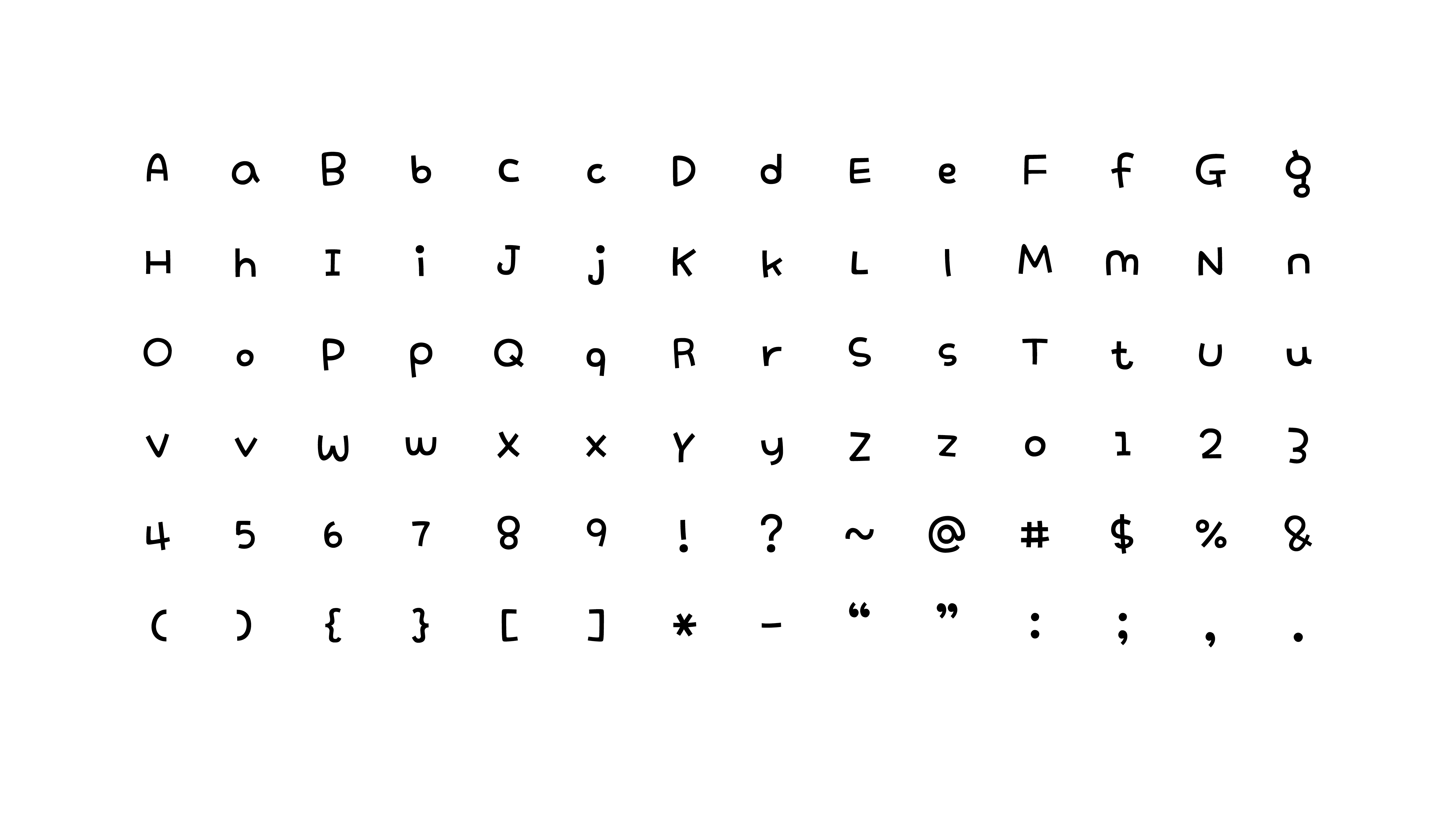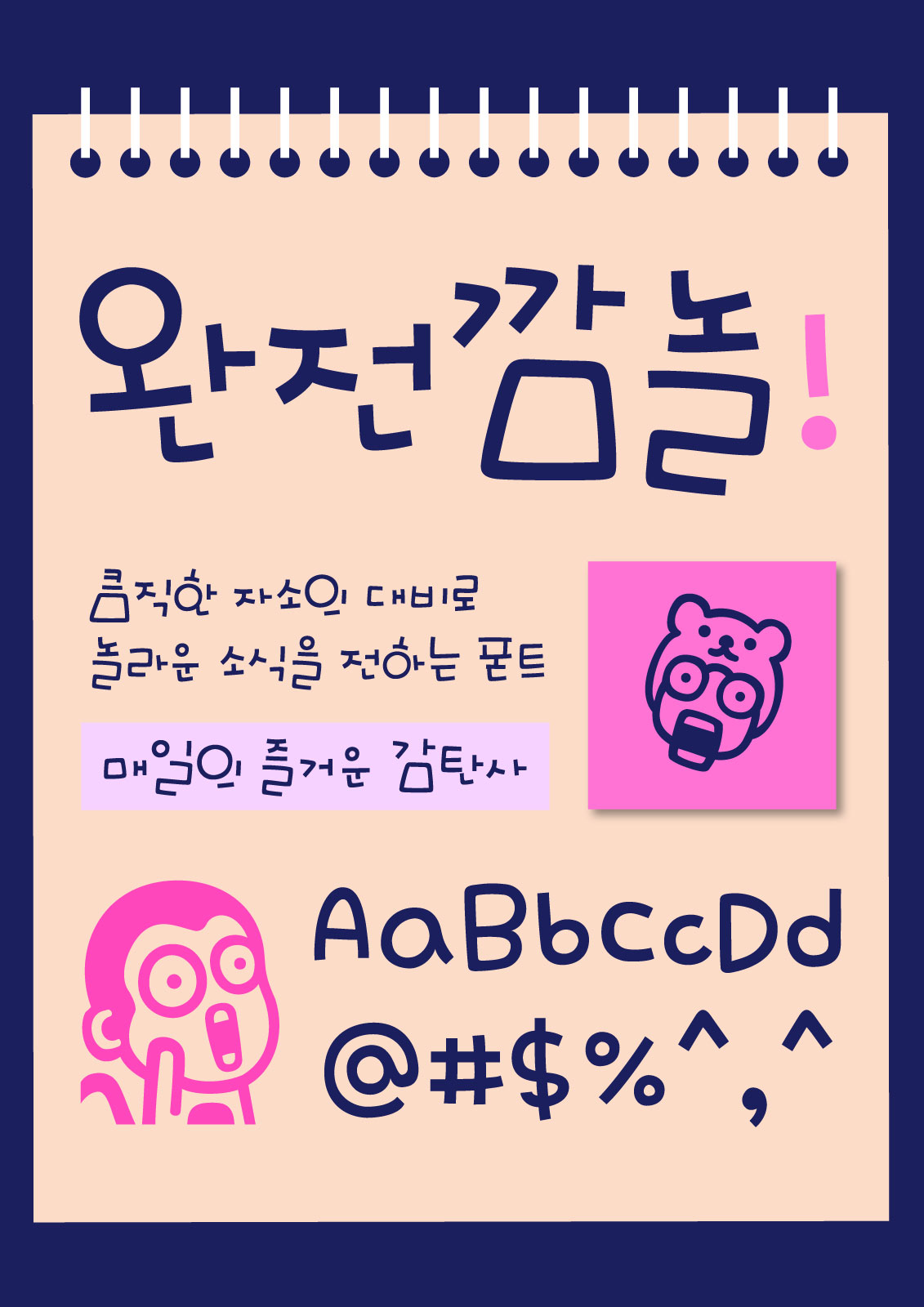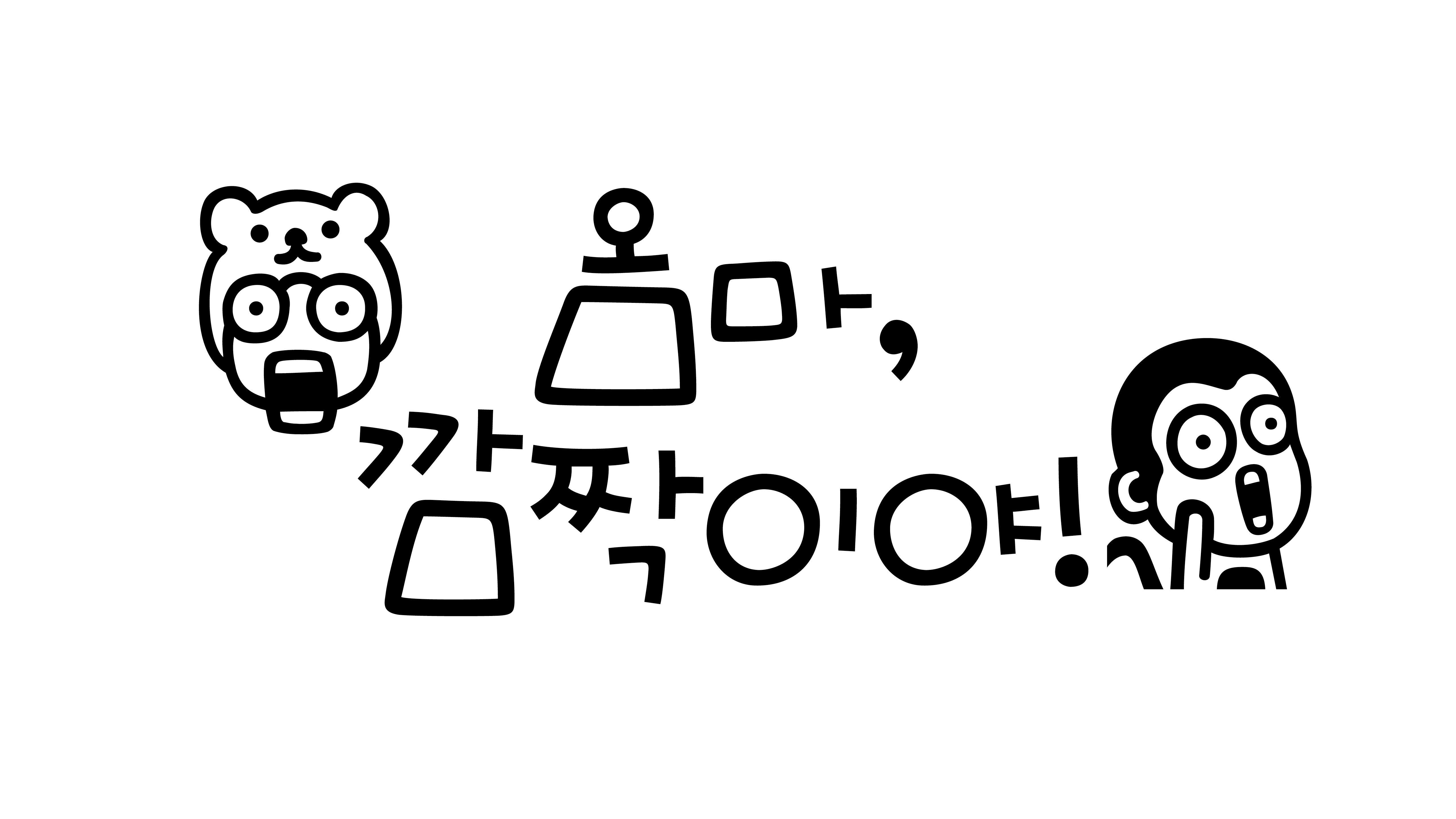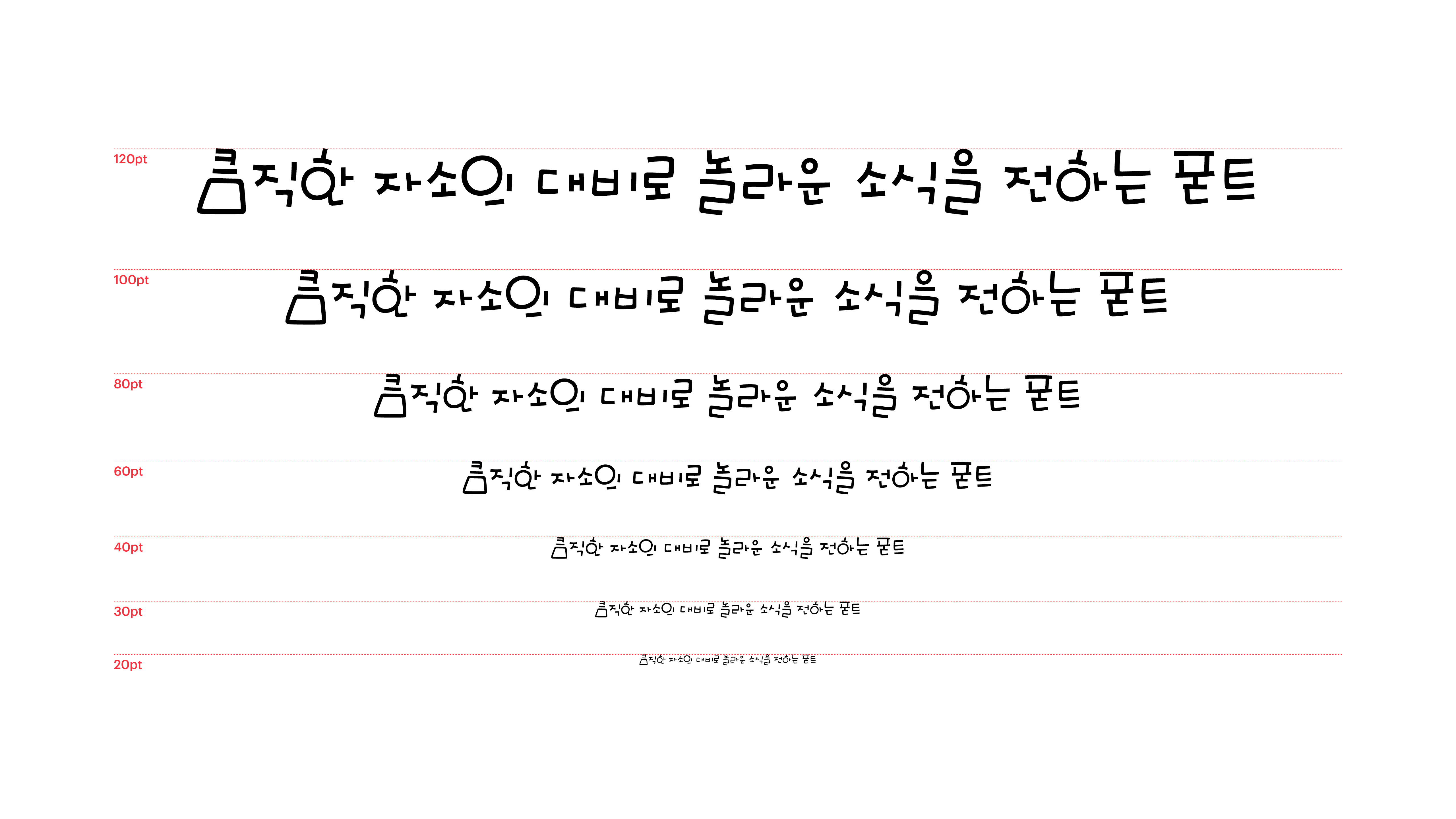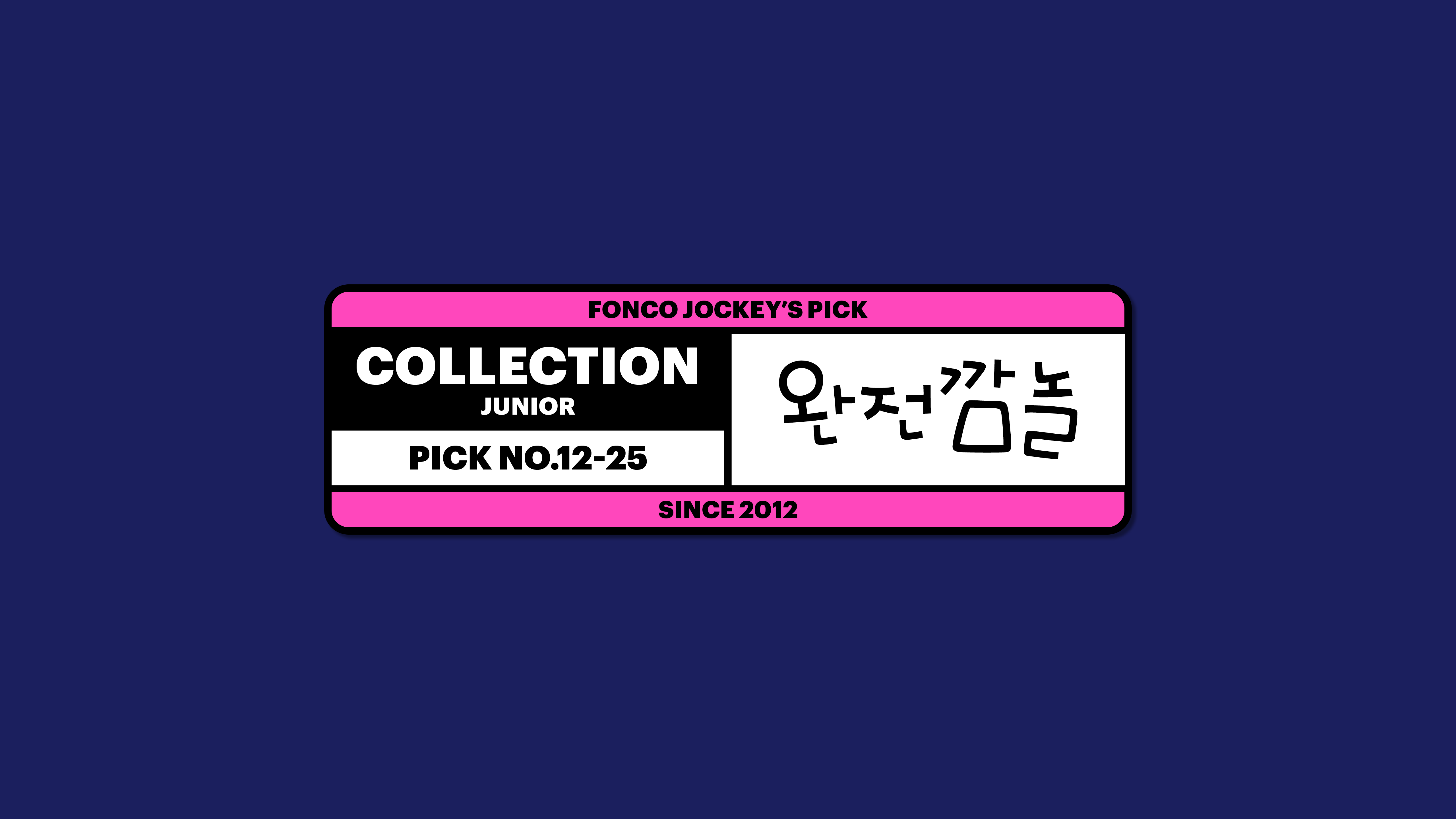
완전깜놀
Yoon 완전깜놀
세상에는 깜짝 놀랄 일이 참으로 많습니다. 그런데 이왕 놀랄 거라면, 좋은 일로만 놀랐으면 좋겠어요. 완전깜놀체는 놀라울 정도로 즐거운 소식과 축하하고 축하받을 일이 많아졌으면 좋겠다는 바람을 큼직한 자소의 대비에 담아낸 폰트입니다. 매일의 즐거운 감탄사, 완전깜놀체에게 맡겨주세요!